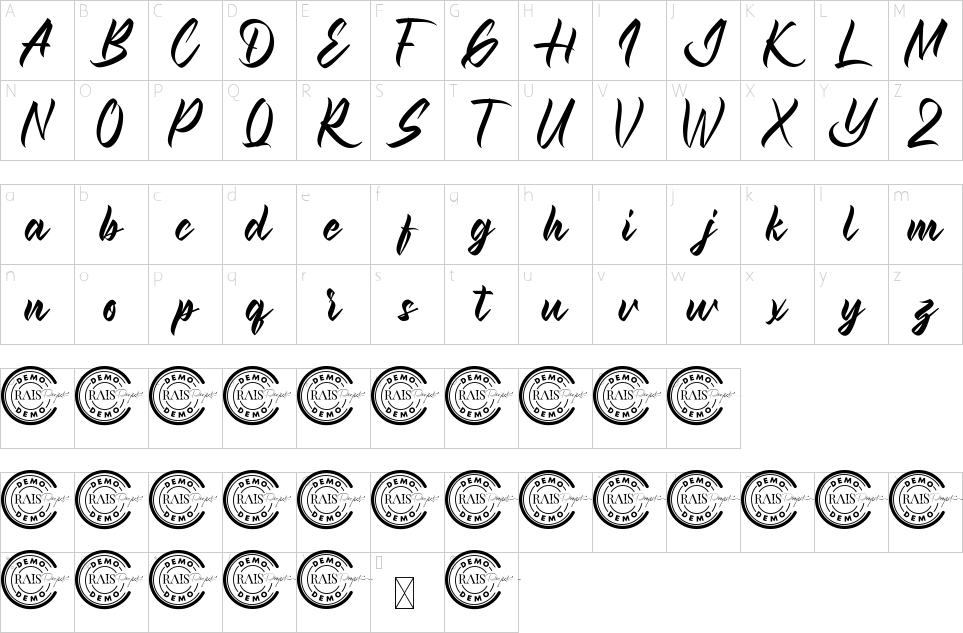
A fonte Marysville é uma opção gratuita e versátil para designers gráficos e escritores de texto, ideal para qualquer projeto que necessite de uma tipografia natural e envolvente. Desenvolvida pelo designer não informado, a Marysville traz uma abordagem elegante e moderna, combinando elementos de fontes clássicas e contemporâneas para criar um resultado único e atraente. Download a Marysville para Windows e Mac, uma fonte que não apenas atende a necessidade de estilo e versatilidade, mas também é uma opção incrivelmente acessível, já baixada 1,613 vezes. Com seu design cuidadosamente refinado, a Marysville se destaca como uma fonte que combina perfeitamente tanto para criações digitais quanto para projetos impressos.